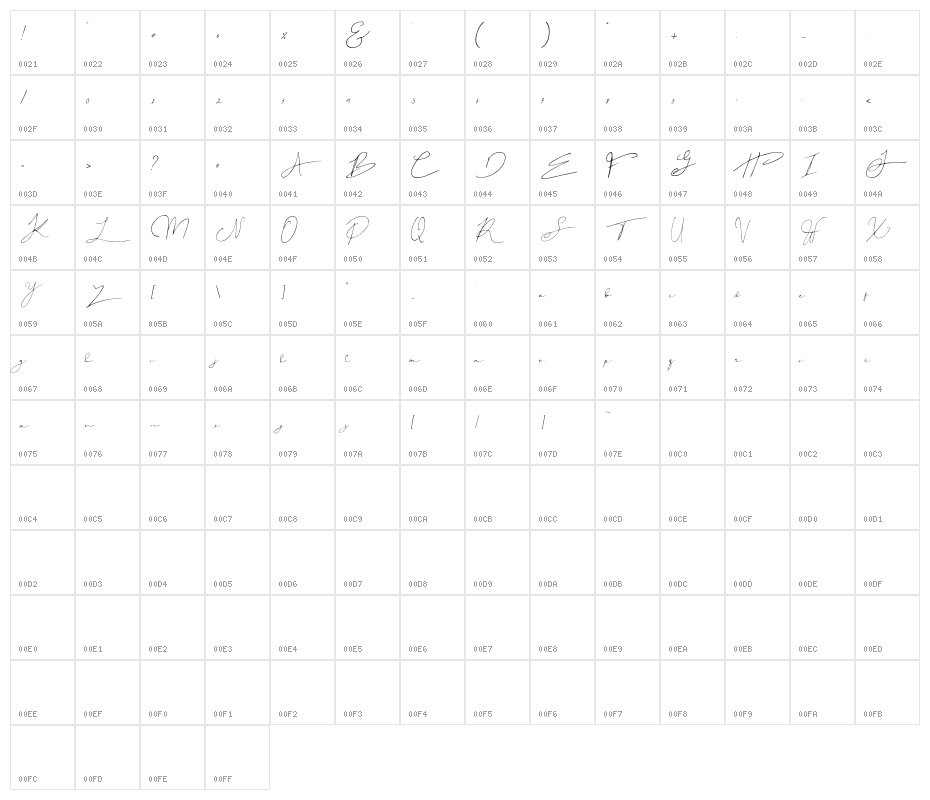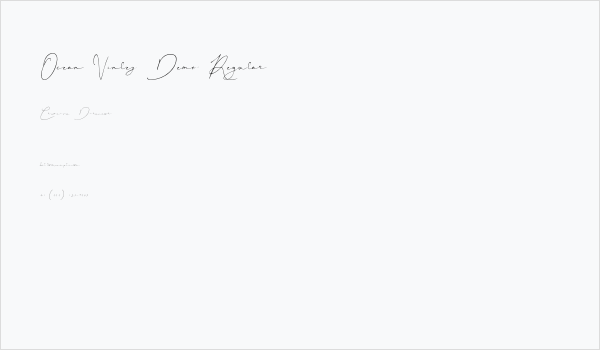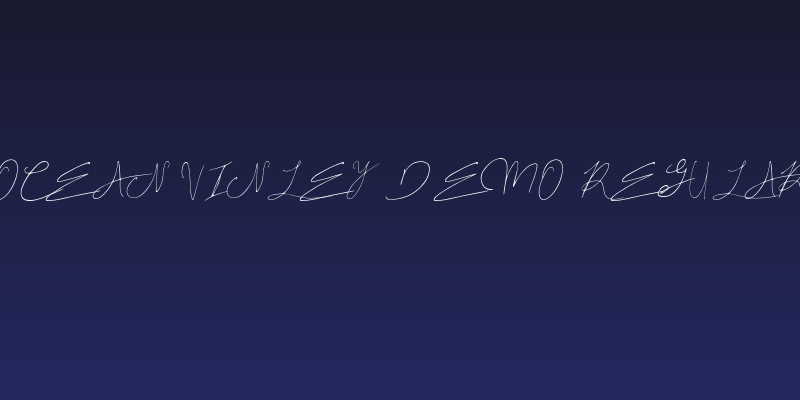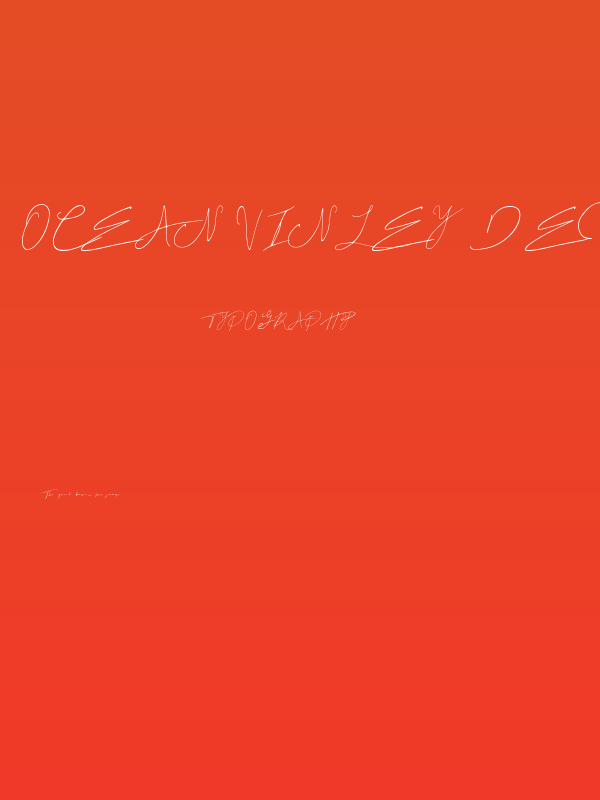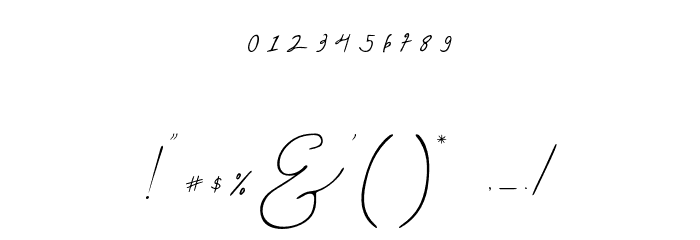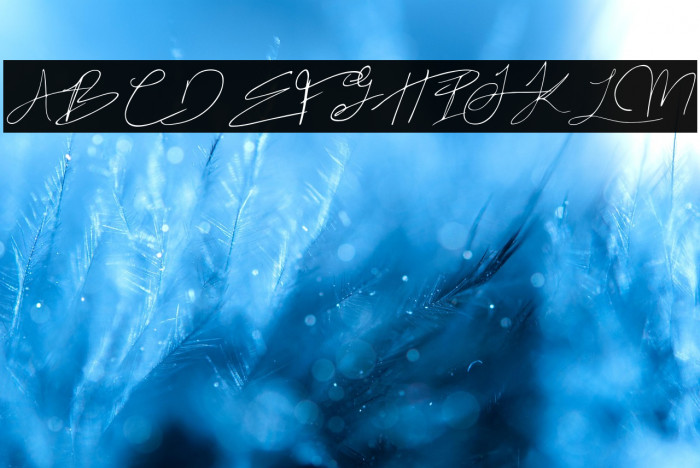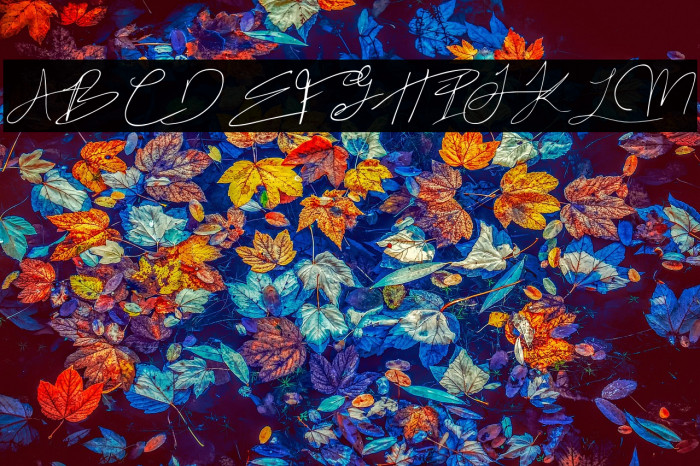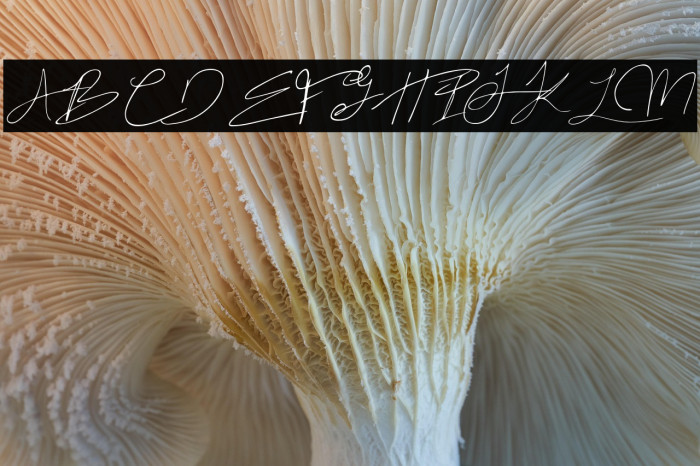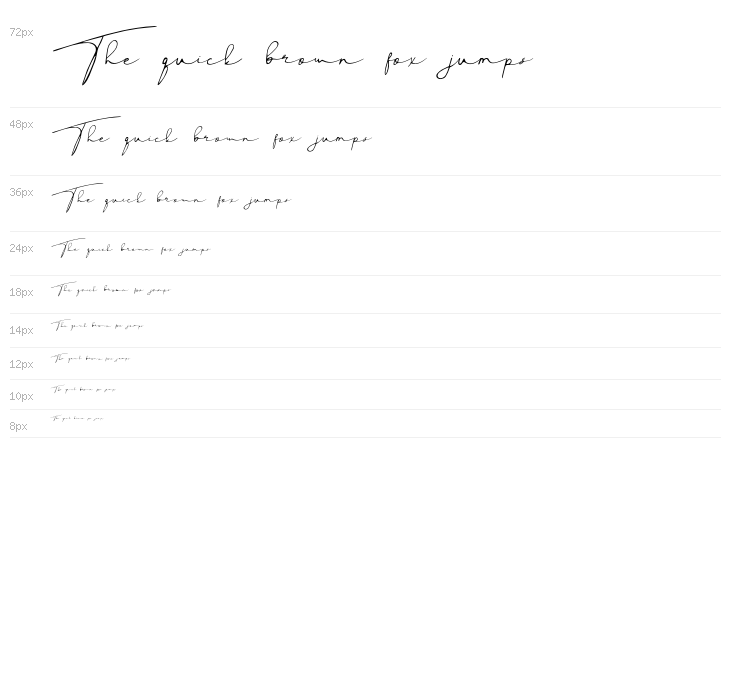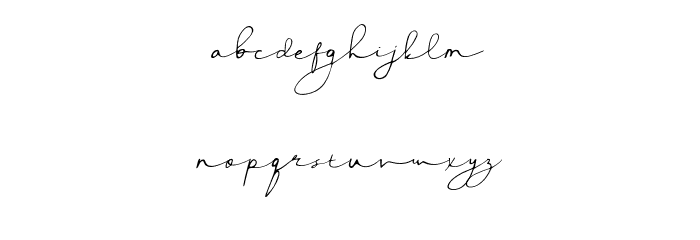
Ocean Vinley Demo Regular Font
| Gesamtstil | Elegant, Decorative |
| Anwendungsfall | Logos, Invitations, Branding |
| Vorgeschlagene Projekte | Ideal for wedding invitations, elegant branding, personal stationery, and high-end product packaging. |